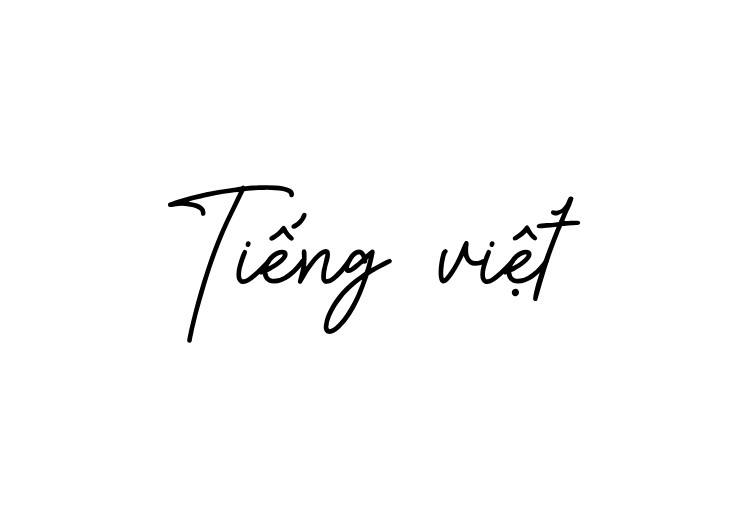
Hệ thống font MJ là một tập hợp các phông chữ đã được tối ưu hóa hiển thị tiếng Việt, bao gồm nhiều phong cách từ hiện đại, tối giản đến nghệ thuật viết tay lãng mạn. Việc sử dụng các bộ phông chữ MJ giúp các kiến trúc sư và nhà thiết kế trình bày hồ sơ dự án, phối cảnh homestay hay bộ nhận diện văn phòng container một cách linh hoạt, tránh tình trạng lỗi dấu ký tự.
Sức hút thẩm mỹ của hệ thống phông font MJ Việt hóa hiện nay
Điểm lôi cuốn đặc trưng của dòng phông MJ nằm ở sự tỉ mỉ trong khâu xử lý bảng mã Unicode, giúp các dấu thanh luôn cân đối với cấu trúc chữ gốc. Dù bạn chọn phong cách font MJ Kobe vững chãi hay các kiểu chữ viết tay mềm mại, văn bản vẫn duy trì được nhịp điệu thị giác ổn định. Sự đa dạng của MJ cho phép người dùng thay đổi ngôn ngữ thiết kế một cách nhanh chóng, phù hợp với tinh thần của từng hạng mục công trình từ phong cách công nghiệp đến mộc mạc.
Sự ổn định của các bộ phông này còn thể hiện qua khả năng truyền tải cảm xúc và định hình cá tính thương hiệu. Việc ứng dụng font MJ Milestone hay MJ Charming Valentine giúp các tiêu đề phối cảnh trở nên có hồn hơn, tạo ra sự kết nối về mặt thị giác đối với chủ đầu tư. Đây là giải pháp hiệu quả cho những dự án đề cao sự riêng biệt, sự tinh tế và tư duy thiết kế hiện đại trên cả nền tảng kỹ thuật số và ấn phẩm in ấn.
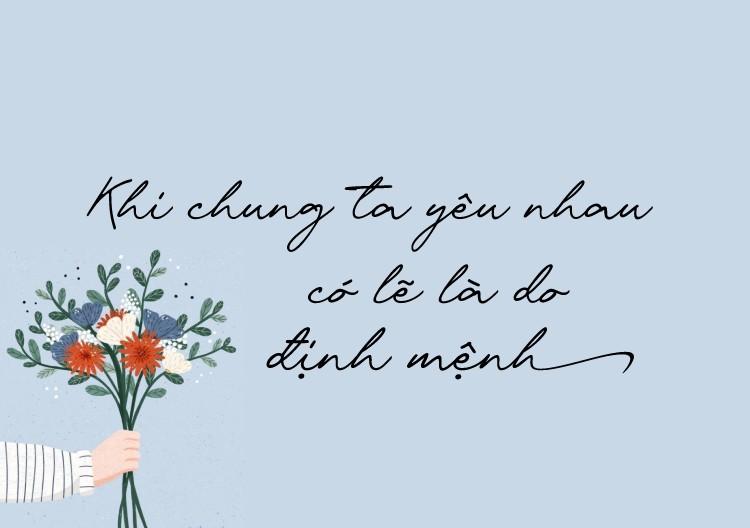
| Biến thể phông MJ | Đặc tính thiết kế | Ứng dụng phù hợp |
|---|---|---|
| MJ Milestone / Charming Valentine | Script nghệ thuật, nét bút bay bổng | Logo homestay, thiệp mời cao cấp |
| MJ Kobe / The Hustle | Sans-serif hiện đại, gọn gàng, dứt khoát | Bản vẽ kỹ thuật, hồ sơ năng lực |
| MJ Chalkduster | Nét phấn viết bảng thô mộc, tự nhiên | Decor quán cafe, biển bảng sáng tạo |
| MJ Whitegone / Bygonest | Phong cách hoài cổ, Retro, tinh tế | Biển tên resort, poster di sản |
| MJ Maritime | Phong cách biển cả, phóng khoáng | Nhận diện du lịch, khu nghỉ dưỡng |
Tư vấn trình bày: Để bản thiết kế đạt được hiệu quả thị giác hài hòa, bạn nên sử dụng các dòng font MJ kobe cho phần nội dung thuyết minh chi tiết nhờ độ rõ nét cao. Đối với các điểm nhấn nghệ thuật hoặc tiêu đề trang mục, việc phối hợp cùng font MJ milestone sẽ giúp tổng thể bố cục trông chuyên nghiệp và có gu thẩm mỹ riêng.
03 Ứng dụng phông chữ MJ vào thực tế công trình
Nhờ diện mạo đa năng và giàu tính thẩm mỹ, bộ phông chữ này mang lại giá trị thực tế cao trong khâu quảng bá và hoàn thiện các không gian sống hiện đại:
- Hệ thống nhận diện cho Homestay & Boutique Hotel: Những nét chữ từ font MJ maritime hoặc MJ Bygonest rất ăn ý khi xuất hiện trên chất liệu gỗ hoặc alu phủ màu trầm. Phông chữ này giúp không gian toát lên vẻ thư thái, thu hút khách lưu trú yêu thích phong cách sống gần gũi thiên nhiên.
- Trình bày hồ sơ dự án chuyên sâu: Sử dụng font MJ the hustle cho các tiêu đề báo cáo tiến độ giúp hồ sơ dự án nhà lắp ghép trông mạch lạc, thể hiện sự chuyên nghiệp và năng động của đơn vị thi công đối với chủ đầu tư.
- Trang trí nội thất và bảng hiệu Decor: Bạn có thể dùng font MJ chalkduster để in decal trang trí hoặc làm bảng thực đơn tại các khu văn phòng container, tạo điểm nhấn đầy thẩm mỹ và khơi gợi cảm hứng sáng tạo cho nhân viên.
03 Lưu ý kỹ thuật khi thiết kế với bộ font MJ Việt hóa
Để khai thác hiệu quả vẻ đẹp của dòng font đa dạng này mà không làm rối mắt người xem, người thiết kế nên lưu tâm một số kinh nghiệm sau:
- Kiểm soát khả năng đọc hiểu: Với các kiểu chữ Script như font MJ beautiful athellin, bạn nên ưu tiên sử dụng cho tiêu đề ngắn hoặc cụm từ nhấn mạnh. Tránh dùng cho các đoạn văn bản dài vì sẽ gây mỏi mắt cho người đọc.
- Lựa chọn kích thước hiển thị: Đối với các phông mang phong cách mộc mạc như font MJ whitegone, hãy kiểm tra độ sắc nét của bản in thử để điều chỉnh độ dày nét phù hợp, đảm bảo các chi tiết nhỏ không bị nhòe mờ khi thi công thực tế.
- Phối hợp font chữ đồng bộ: Hãy giới hạn sử dụng tối đa 2 đến 3 loại phông MJ khác nhau trong cùng một ấn phẩm để duy trì tính nhất quán cho bộ nhận diện thương hiệu công trình.